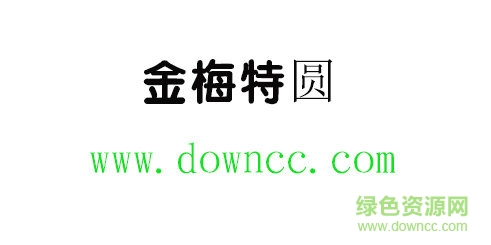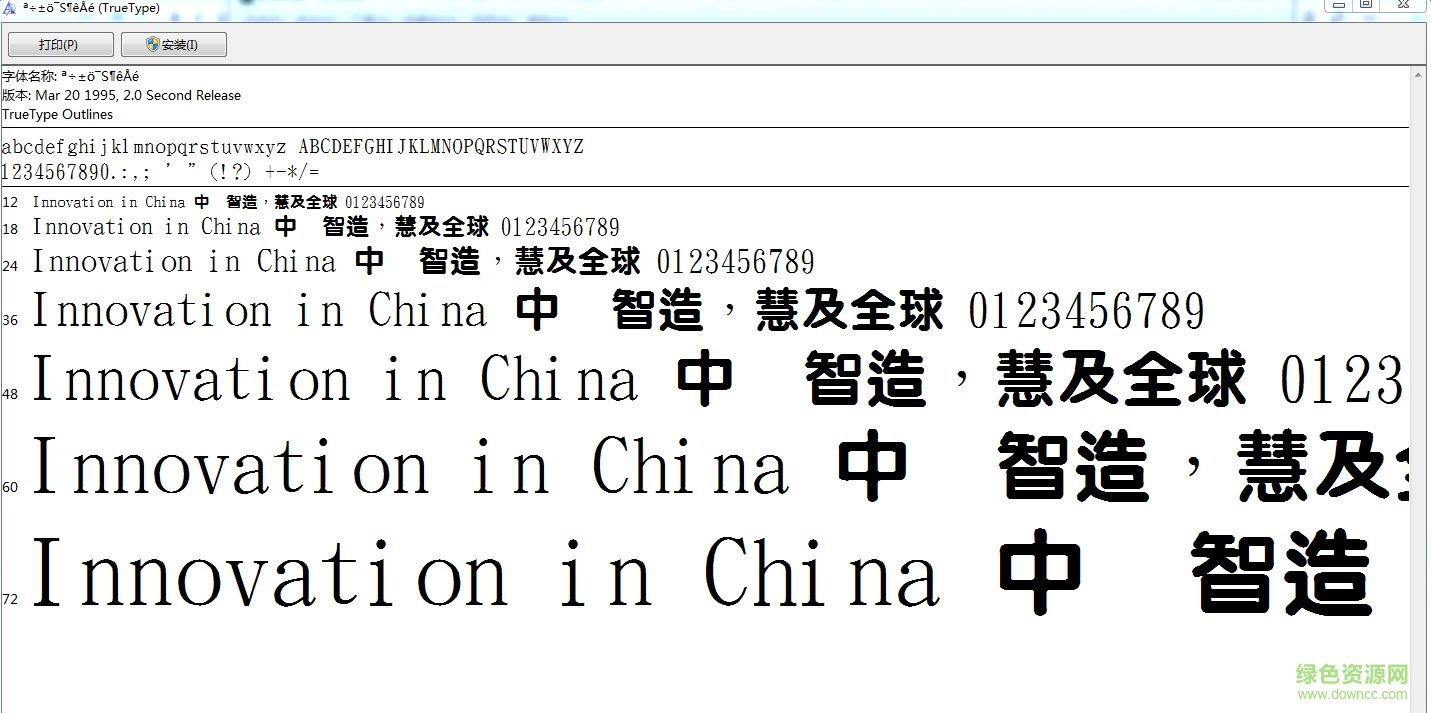
金梅特圓體字體是一款迷你金梅類圓體字體軟件,是書法家們創(chuàng)作時必須的字體之一,其形式非常亮眼突出,能夠突出文章中的重點(diǎn)信息內(nèi)容,用于設(shè)計(jì)廣告詞句等都是不錯的選擇,感興趣的朋友就快來綠色資源網(wǎng)下載使用吧!
金梅特圓體是一款金梅類圓體字體,字體效果比較圓滑,喜歡圓滑字體的朋友可以下載使用看看效果如何。